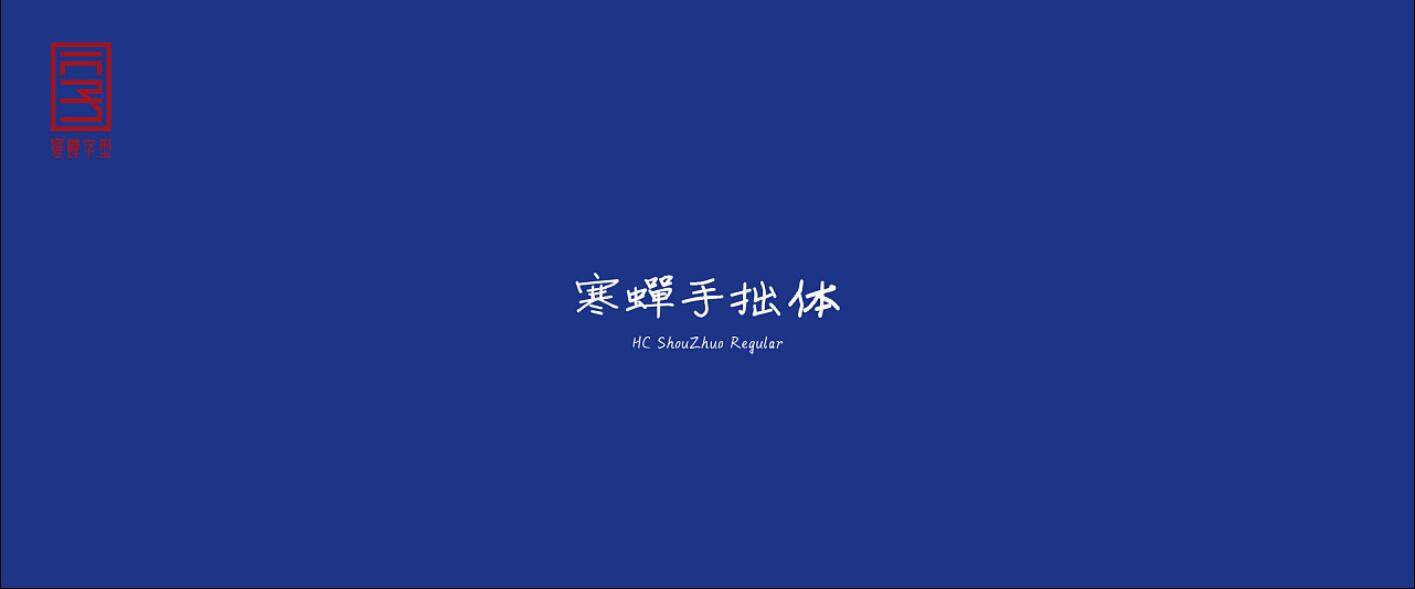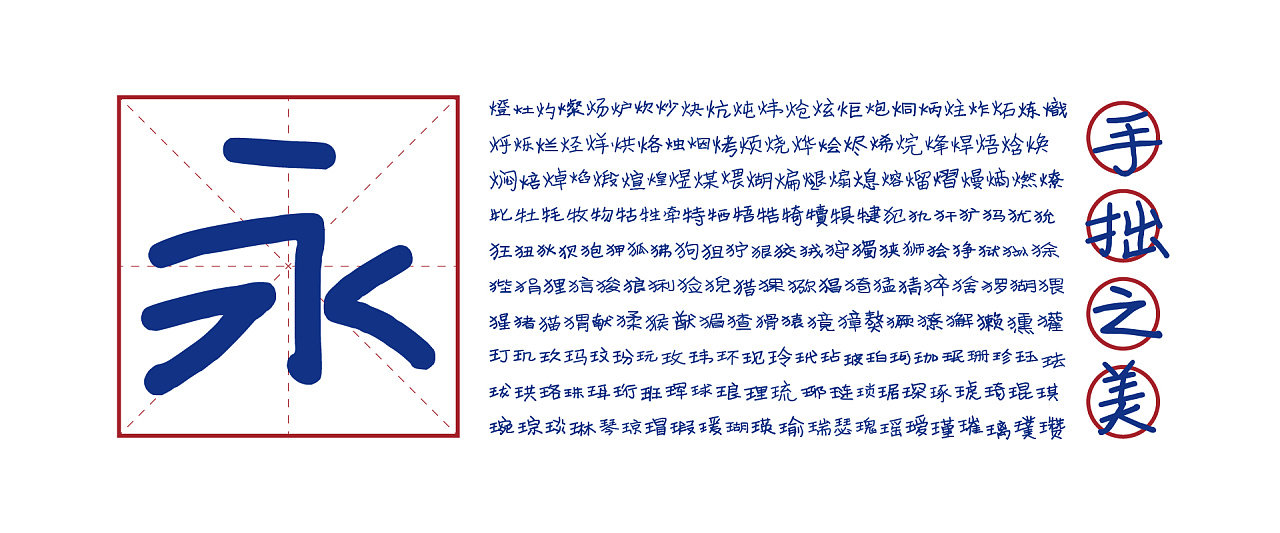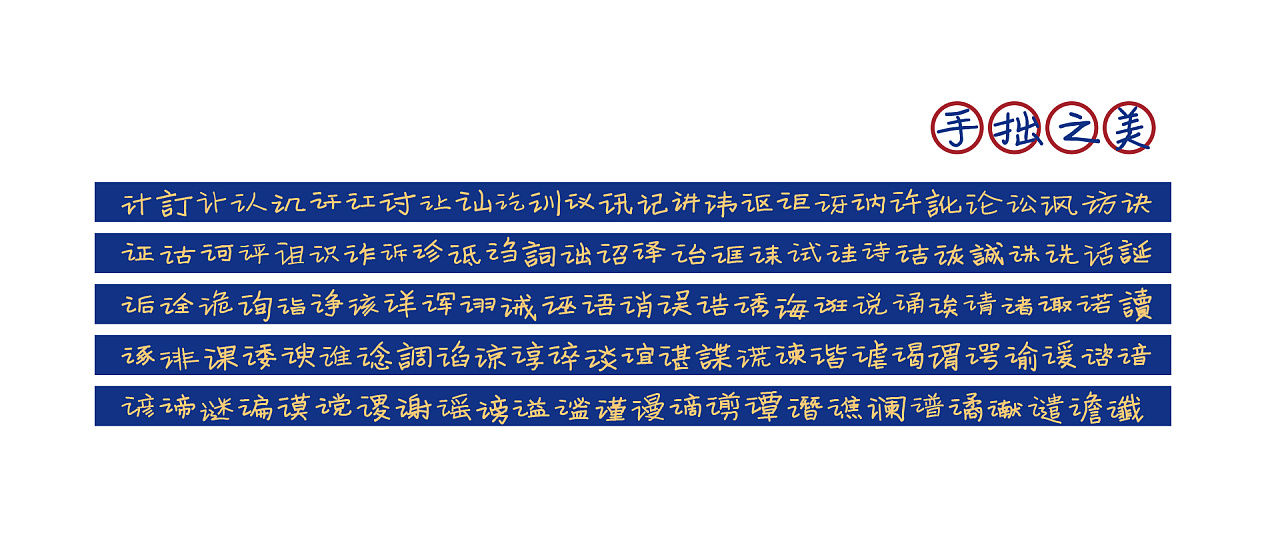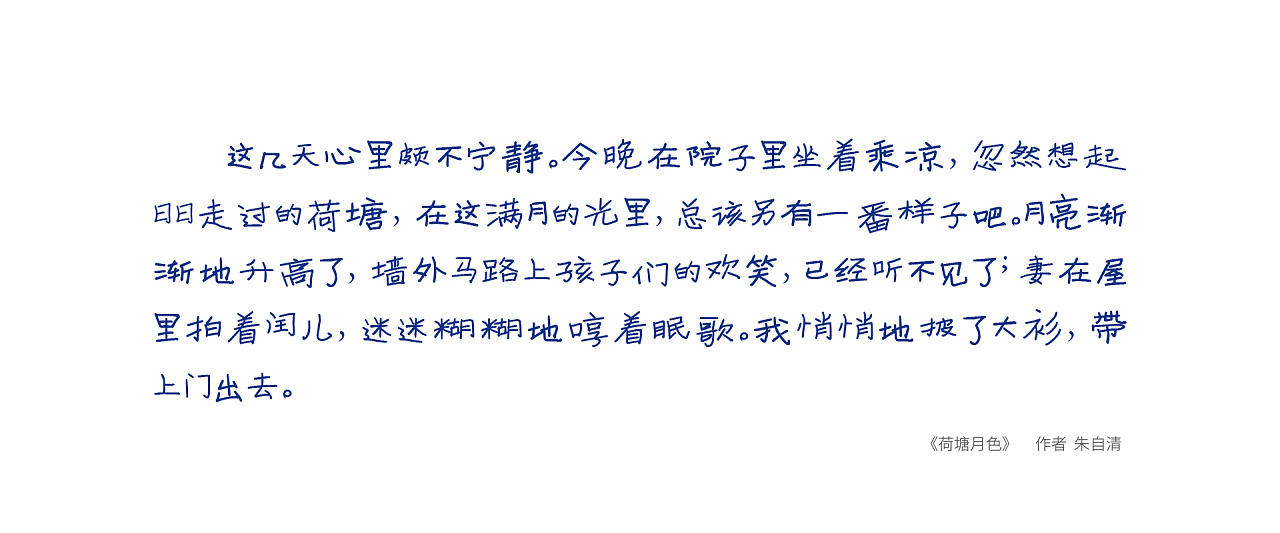
寒蝉手拙体,其核心精髓在于深入挖掘手写字体中自然流露的手拙之美,这种美感源于真实书写时的偶然与不完美。字体设计刻意模仿了墨色浓淡的变化、笔画边缘的轻微毛糙以及结构上不经意的歪斜,从而营造出一种高度逼真、仿佛亲笔书写般的视觉体验。它让人联想到纸笔之间直接而朴素的对话,摒弃了电脑字库常见的工整与冰冷。虽然因其鲜明的风格特点,其应用范围相对有限,主要用于艺术设计、文学作品封面、独立杂志或个人化表达等场景,但在这些领域中,它却具备着不可替代的独特价值与强烈的情感表现力。 这套字体的每一处细节,都凝聚着设计师的匠心,旨在通过模拟手写的笔意和随性的结构,来构建一套风格独特、自成一派的小众字体。它并非追求完美无瑕的工业制品感,而是致力于捕捉那份手工制作独有的温度与韵味。本字体严格按照《中华人民共和国国家标准GB2312-80》字符集标准进行设计与收录,确保了其在中文简体环境下的广泛适用性。为了满足不同平台与设计软件的需求,寒蝉手拙体同时提供了主流的TrueType和OpenType两种字体格式,共完整收录字形7586个,涵盖了标准中绝大多数常用汉字及符号,为使用者提供了扎实而全面的字形支持。